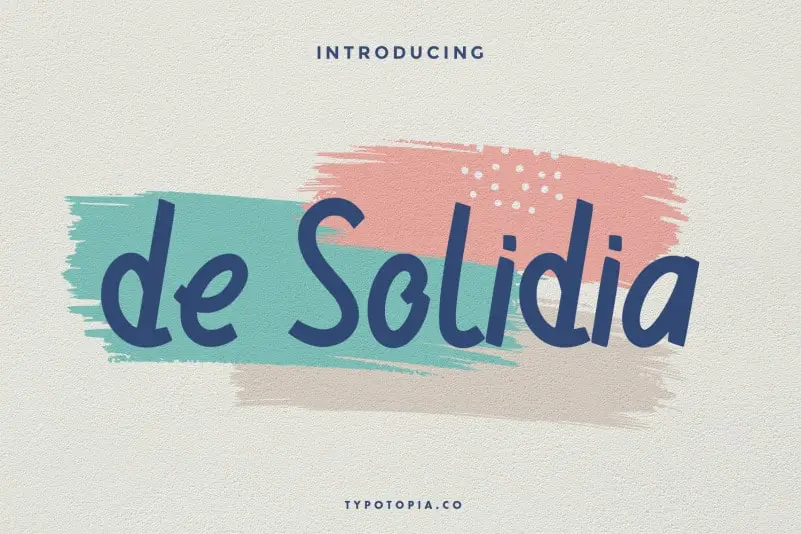
De Solidia Handwritten Font – Download Grátis
Introduzimos a Fonte Handwritten De Solidia Font. Esta fonte é perfeitamente projetada para uma aplicação especializada, especialmente para identidades visuais, moda, cartões de papelão, revistas, menus e convites, livros e embalagens, entre outros ambientes gráficos onde o arco-íris e a personalidade são fundamentais. Com seu estilo livre, De Solidia Handwritten é uma escolha perfeita para quem busca um toque único e elegante em projetos decorativos, seja para criar cartões de convite ou editoriais fashionistas, ou até mesmo para dar vida aos rótulos de embalagens. Seja você designer gráfico, publicitário ou editor, De Solidia Handwritten é uma fonte que adicionará sofisticação e personalidade à sua arte.